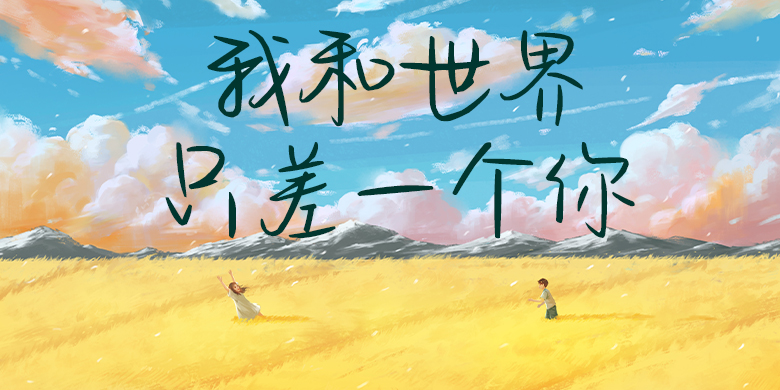
方正手迹-我和世界只差一个你
方正手迹-我和世界只差一个你,这款字体结构工整、笔画清晰,兼顾美观与易读性,适用于标题、正文、海报、包装、LOGO 等多种场景。字形优雅稳定,风格百搭耐看,适配日常排版与创意设计,让文字呈现更舒适、更具质感。方正手迹-我和世界只差一个你一笔一画,皆是细节,以均衡的比例、流畅的线条打造舒适视觉体验,字形端正大气,风格简约现代。无论是商业设计、品牌宣传还是日常排版,都能轻松驾驭,让文字更有格调与力量。方正手迹-我和世界只差一个你字体下载。
我和世界只差一个你是一款风格鲜明独特的手写体。该字体整体比较随性,笔画曲线较多,把转折设计成圆润的弧线,使字体增添更多可爱有趣的感觉。该字体适用于文艺类的书刊、品牌广告和产品包装设计,以及社交网络的个性化用字。